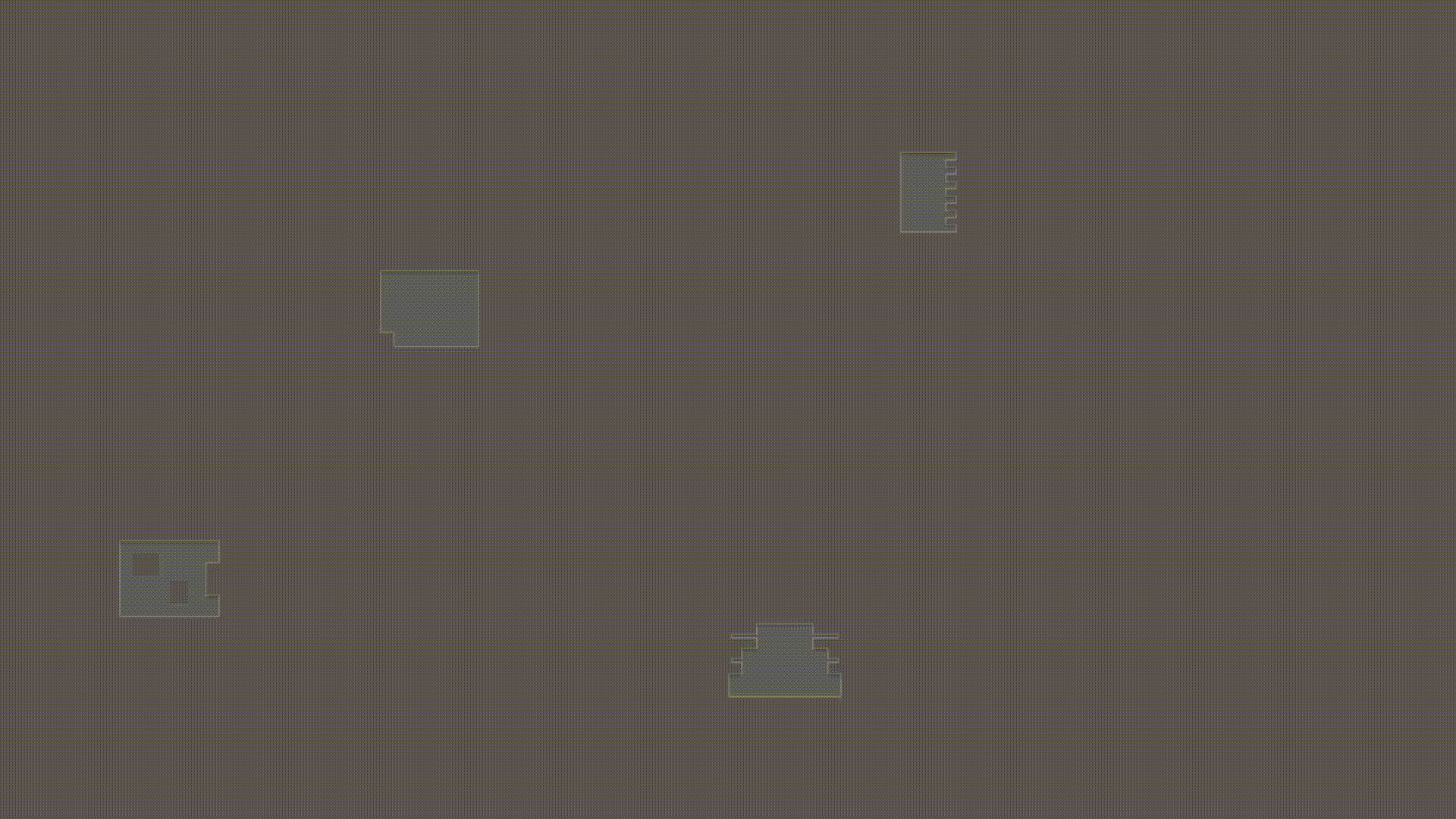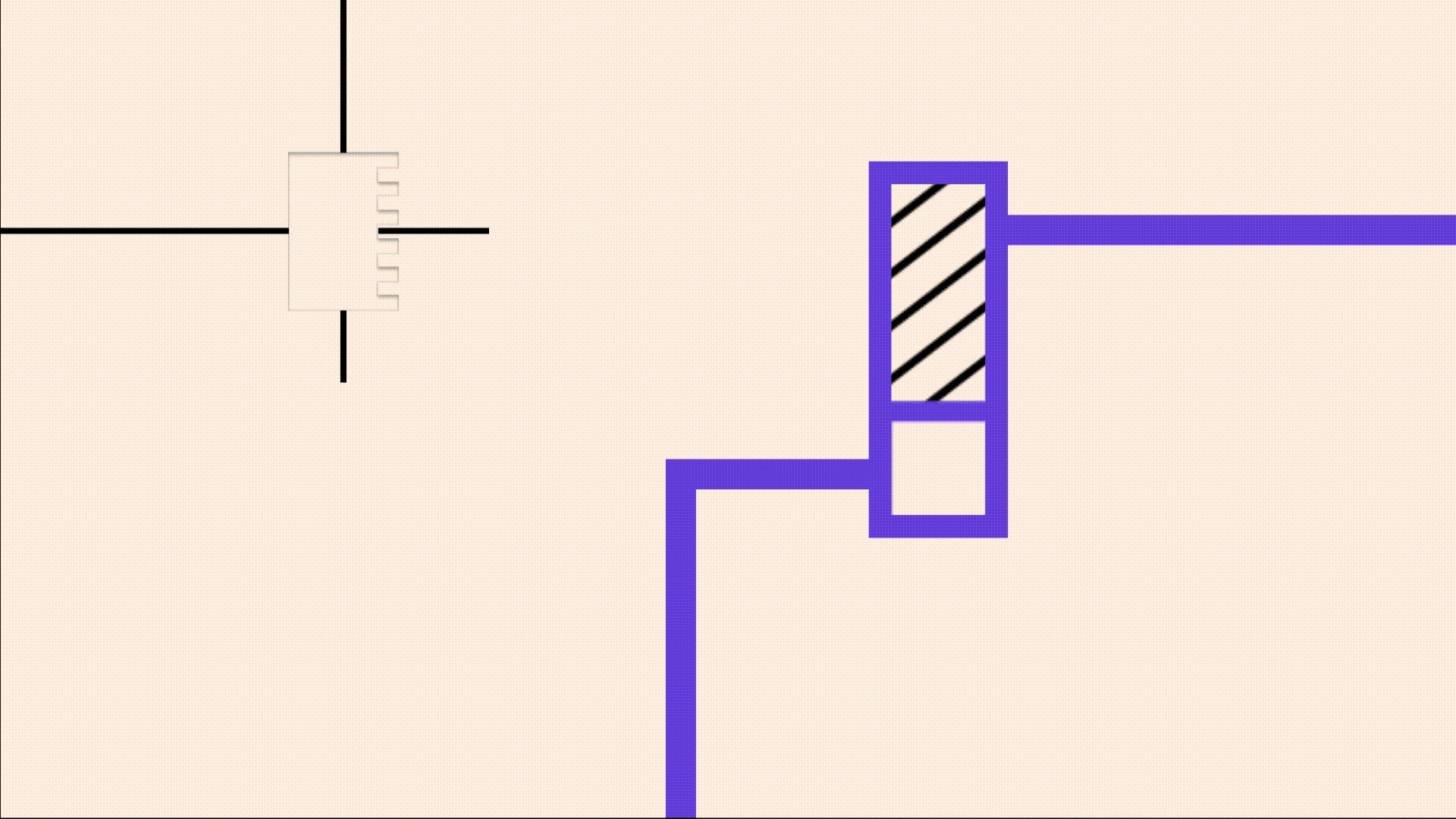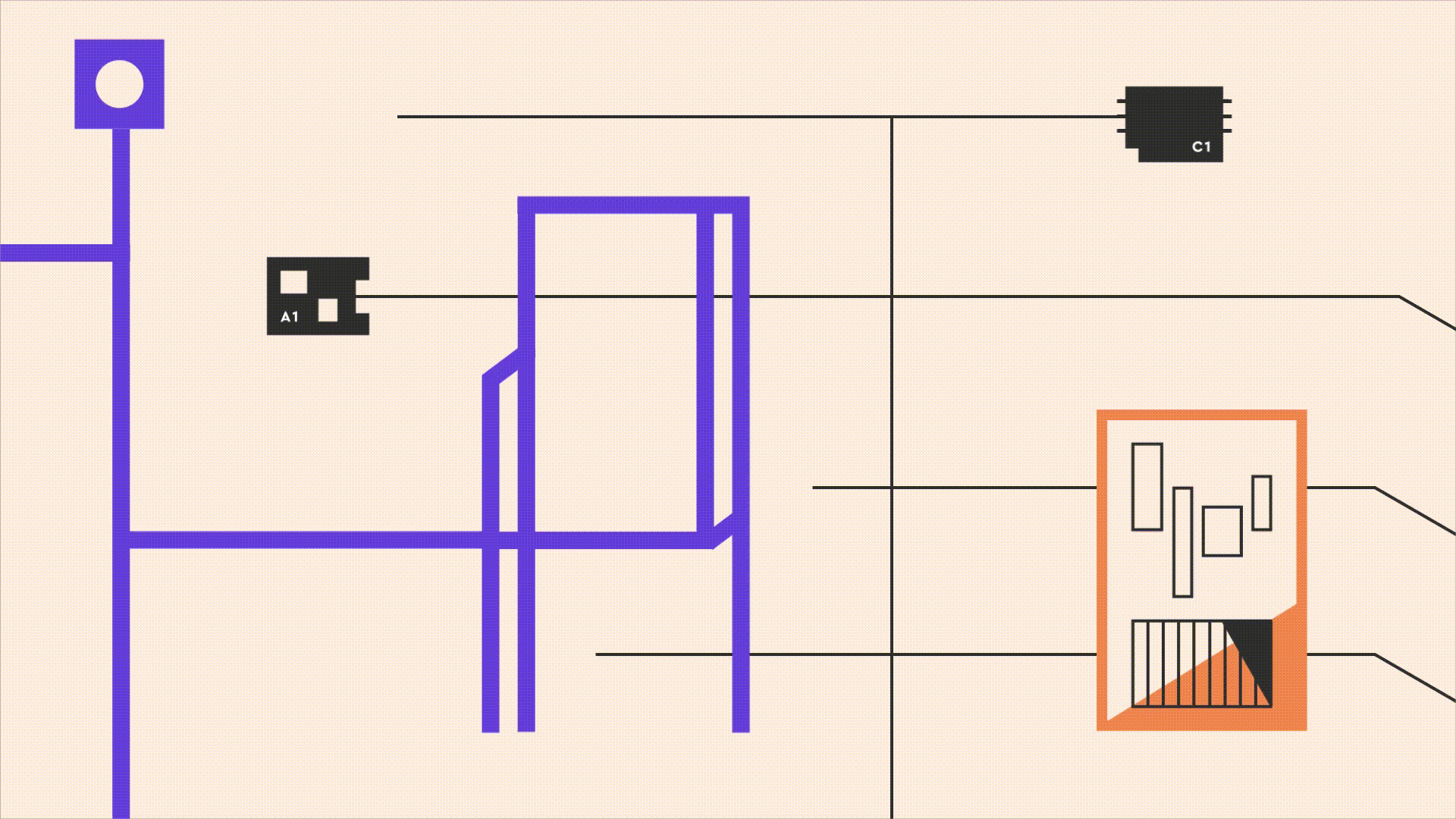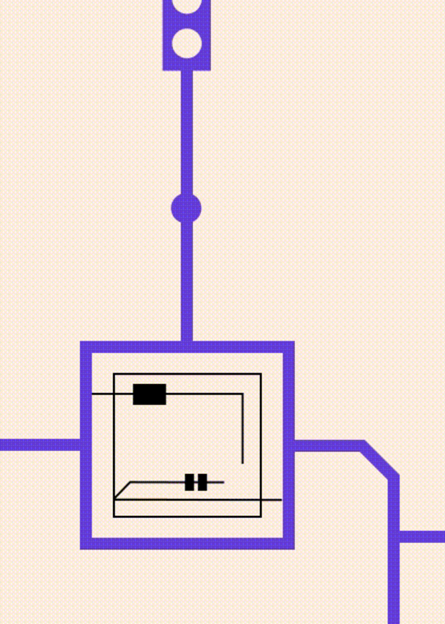
System — акцидентный геометрический шрифт. В основе проекта лежит эстетика печатных плат и аппаратной логики.
Структура образует жесткий каркас, текст превращается в непрерывный процесс: буквы конструируются жестко, работая как маршруты, по которым передается информация через провода.